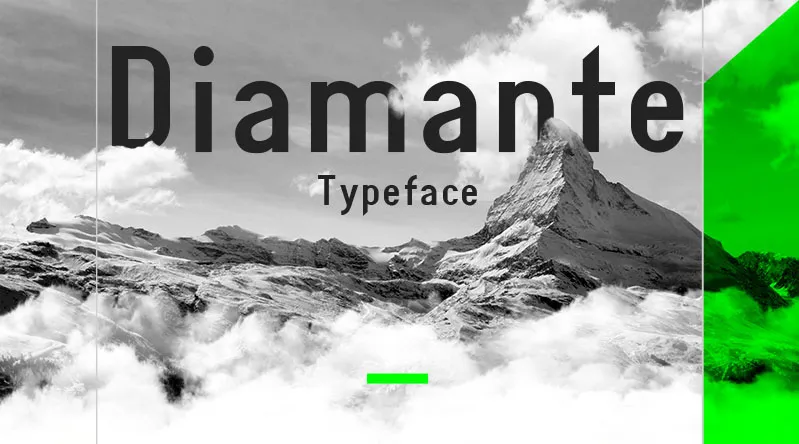
Diamante Typeface – Download Grátis
A Diamante é uma nova escolha para quem procura uma tipografia sans-serif geométrica com um ar forte e funcional. Essa fonte foi criada usando formas geométricas simples, combinadas com cortes 45 graus nas linhas de texto, tornando-a perfeita tanto para uso em apresentações quanto para aplicação em revistas ou jornais. Suas características foram ampliadas para incluir linguagens da Europa do Leste, garantindo que essa fonte seja adaptável a um amplo espectro de ambientes de design — desde o grande formato das capas de livros até os layouts mais elaborados. Seja você uma designer de jornal ou editora de pequenos livros, a Diamante tem o potencial de se tornar uma aliada útil em seu trabalho diário. É perfeita para quem busca um equilíbrio entre simplicidade e força na design tipográfico.